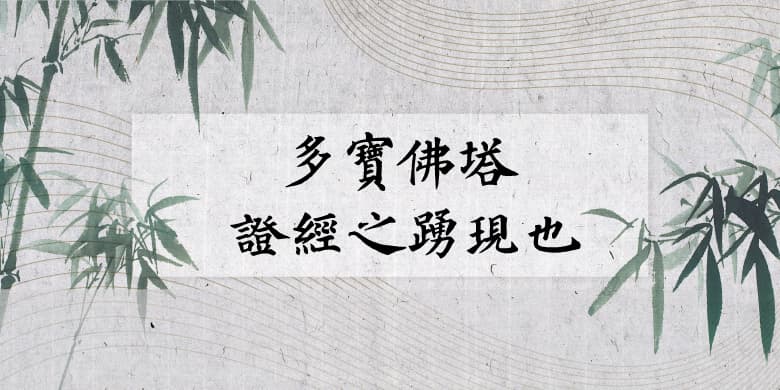
《多宝塔碑》,全称《大唐西京千福寺多宝佛塔感应碑》,是唐天宝十一年(752年)由当时的文人岑勋撰文、书法家徐浩题额、书法家颜真卿书丹、碑刻家史华刻石而成,是楷书书法作品。现今保存于西安碑林第二室。颜真卿与赵孟頫、柳公权、欧阳询并称为“楷书四大家”。又与柳公权并称“颜柳”,被称为“颜筋柳骨”。代表作品有《多宝塔碑》《颜勤礼碑》《祭侄文稿》等。
《多宝塔碑》整篇结构严密,字行间有乌丝栏界格,其结体宽博,布白较匀整,字型稍方,端庄平稳,正气饱满,布势均匀,四周撑满,故气势雄伟,这是“颜体”佛书的又一特色。颜真卿的结体,用的是“外拓”笔法,字势方正,撇捺竭力向左右拓展,气势尤其是博大恢弘。无论独体字,还是合体字,都以中心轴线为重心,在结构处理上,既讲究规矩,又生动活泼。在楷书史上还没有一个人有过这样的结体方式,尤其是捺脚,重拙而不作波曳之状,线条涩重雄强,气概非常。《多宝塔碑》蕴含了“二王”和初唐以来书家的风流,历来为书家珍重。它是唐代“尚法”的代表碑刻之一,学颜体者多从此碑下手,入其堂奥。学子描红、士子举业、居士写经、坊间印书,竞相仿效。至今仍是适用非常广、影响十分巨大的书法作品。
《书体坊多宝塔碑颜体》是书体坊禚效锋以原拓文字为基本,对原拓文字进行描摹、放大、精修,并依照此书法风格,使用拓本中原有的字形和部件进行扩充完善到7000个常用繁体字的书法字形,兼顾了艺术性和实用性,是一款标准颜体“风格秀美”的书法字体。
书体坊禚效锋,七零后。江苏邳州人,爱好书法,致力于书法艺术传承,先后独立制作大篆、楷、行、草(小草、狂草)等风格古代书法名家字体多种,当代书法家字体多种。出版有《狂草字典》等书法工具书。